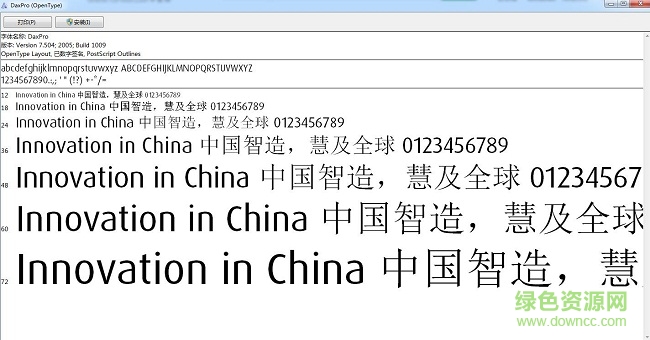
daxpro 字體是一款結(jié)構(gòu)新穎的英文字體,該字體字形簡潔,可讀性佳,給人有一種現(xiàn)代、時尚的感受,適用于雜志、書籍、平面設(shè)計等眾多領(lǐng)域,需要就來下載吧!
【無襯線字體】
1.畫粗細對比小,視覺上看起來基本一致;
2.高度較高;
3.全拋棄裝飾襯線,只剩下主干,造型簡明有力,更具現(xiàn)代感;
4.適用于標題、廣告,瞬間的識別性高。